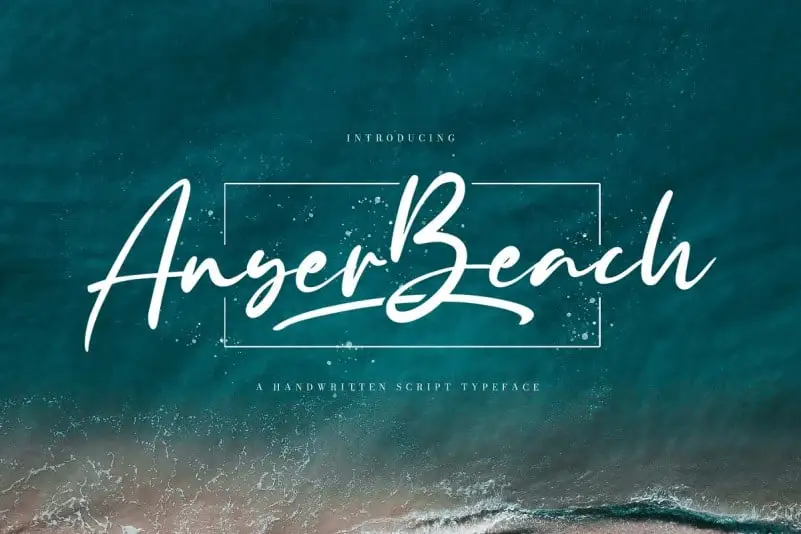
Anyer Beach Script Font – Fonte Grátis
Anyer Beach Script Font
A Anyer Beach Script Font é uma tipografia script baseada em traços rapidamente escritos a lápis. Desenhada para quem busca algo leve, elegante e ondulado, esta fonte possui caracteres encantadores e bem equilibrados. Suas linhas delicadas contrastam perfeitamente com os detalhes mais elaborados das composições, resultando em uma tipografia que se integra a uma ampla variedade de projetos. Inclua Anyer Beach Script na sua ideia criativa e observe como ela transforma esses designs em algo único e vibrante. Seja você um designer buscando dar vida à sua próxima criação ou um artista visual sempre procurando algo novo, Anyer Beach Script é a fonte perfeita. Suas linhas suaves e equilibradas permitem que qualquer projeto toque o seu coração, seja em um design de web, uma capa de livro ou até mesmo em um brochuro de apresentação. Adote Anyer Beach Script para complementar seus mais arrojados conceitos e permita que sua obra prima surja com a sofisticação e delicadeza desta fonte única.